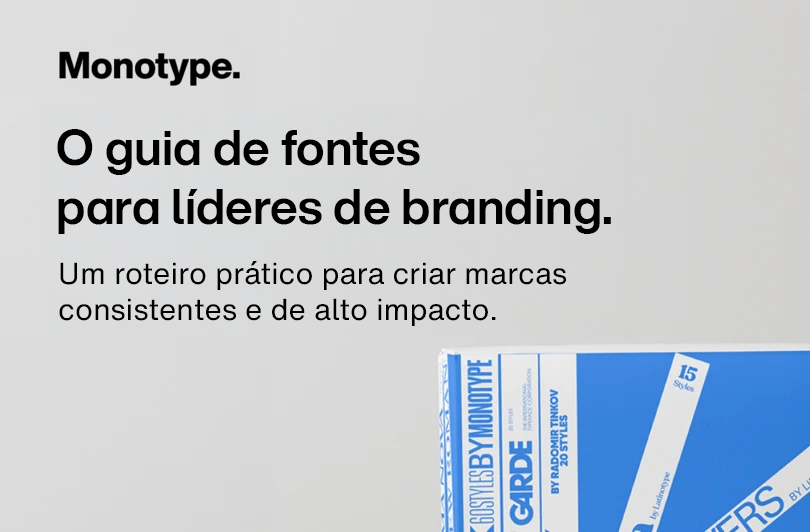
eBook: O guia de fontes para líderes de marcas.
Descubra como a tipografia pode transformar sua marca no Guia do criador de marcas para fontes. Mergulhe no papel fundamental que as fontes desempenham na formação da identidade da marca, no fortalecimento das conexões emocionais e na criação de histórias envolventes. Desde a seleção de fontes personalizadas até a manutenção da consistência entre plataformas, este e-book oferece dicas práticas para elevar a presença da sua marca no cenário competitivo atual.
Destaques do que é abordado no guia:
- A importância das fontes personalizadas na apresentação dos valores e da personalidade da marca
- Como uma tipografia consistente fortalece o reconhecimento da marca em todos os pontos de contato
- Formas como as fontes podem modernizar sua marca, mantendo-se fiéis à sua identidade central
- O impacto emocional da tipografia na construção de confiança e identificação com o seu público